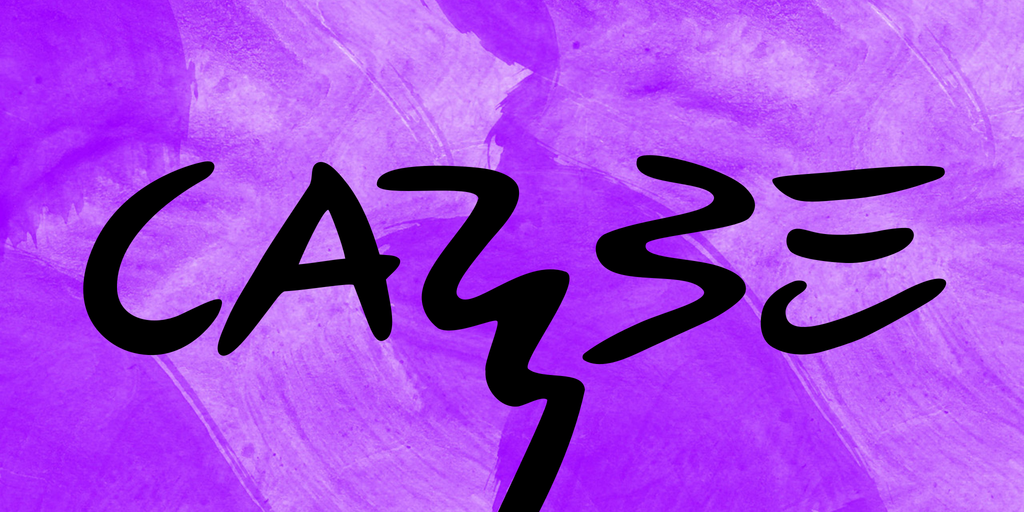
Carybe Font – Fonte Grátis
Carybe Font
Carybe Font é uma fonte tipográfica feita sob a inspiração do traçado distintivo do artista plástico Carybé (1911–1997). Carybé foi um talentoso pintor e escultor cujas obras desafiam as fronteiras da arte, combinando elementos de diferentes estilos ao mesmo tempo. Inspirado por sua rica visão criativa, a Carybe Font oferece linhas fluidas e sutis que refletem o estilo artístico inovador deste gênio do design. Esta fonte não apenas retrata a espiritualidade vibrante da obra de Carybé, mas também oferece uma experiência única de leitura. Suas formas delicadas e a elegância dos traçados são perfeitamente adaptáveis para uso em materiais digitais e impressos, tornando-a útil tanto no design editorial quanto no design gráfico. Uma fonte como esta não apenas ajuda a destacar seu trabalho, mas também faz do texto uma arte por si só. Hamilton é o designer dessa fonte que traduz sua rica influência artística para um formato digital, tornando-o acessível e versátil para projetos de design diversos. Essa Carybe Font é ideal tanto para quem deseja incorporar elementos singulares no seu projeto quanto aqueles que buscam uma fonte de alta qualidade para trabalhos impressos ou digitais.